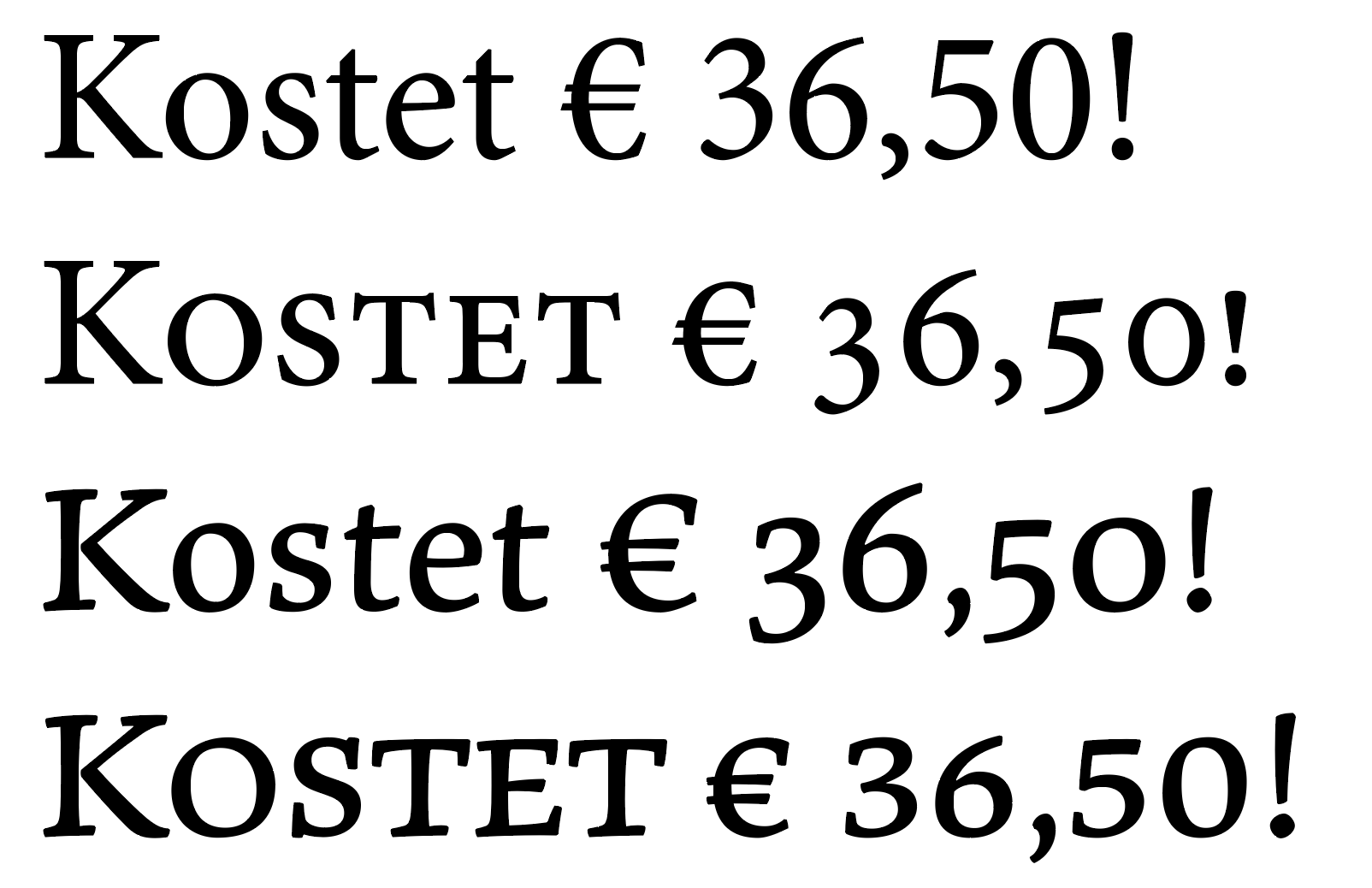
Erwartungen Kapitälchen-Belegung?
Mal ganz dumm gefragt: Was würdet ihr als Schriftanwender alles von einer Kapitälchenbelegung erwarten? Selbstredend sollte jeder Kleinbuchstabe ersetzt werden und der Wechsel auf passende Ziffern ist ebenfalls üblich. Aber danach wird es schnell schwammig. Was würdet ihr noch erwarten oder benötigen?
Eine ganze Menge weiterer Zeichen haben ja auch eher Versalhöhe: Währungszeichen, Satzzeichen, &, % etc. und spätestens bei »Alles in Kapitälchen« würden die dann unschön herausstechen und Kapitälchensatz gegebenenfalls unmöglich machen. Aber spielt das in euren Anwendungen überhaupt eine Rolle?
Ich verwende Kapitälchen eigentlich nur in Literaturverzeichnissen bzw. in Quellenangaben, daher reichen mir die alphanumerischen Glyphen, ggf. mit der üblichen Anpassung, früher ß zu Doppel-S und iota subscriptum zu adscriptum (ich sehe in neueren Schriften das adscriptum zugunsten des subscriptum schwinden, bin da jedoch epigraphisch geprägt).
Absolut. Ich freue mich immer sehr, wenn beim Umstellen auf OpenType → Kapitälchen vom Schriftgestalter (nicht nur die Versalhöhen-Zeichen wie
( ) / ? ! * % usw. mitgedacht wurde, sondern auch die Zeichen wie
+ - — # @ sowie An- und Abführungszeichen.
Versal-ß lasse ich mal wegen der besonderen Brisanz in diesem Forum unerwähnt ;-)
(Ein gutes Beispiel für nützliche diese »case sensive glyphs« ist die kürzlich erworbene Moniker.)
Zudem erwarte ich (ich weiß allerdings gar nicht, ob dass bei der OT-Umschaltung auf Kapitälchen nicht inzwischen ohnehin Standard ist), dass Groß und Kleinbuchstaben dann identische Höhen haben. Anders, als das früher bei vielen Caps-Schnitten (z.B. TheSans Caps) der Fall war.
Und da es selbst bei Foundries wie FontFont keine Selbstverständlichkeit zu sein scheint, bitte dann alles auch für die kursiven Schnitte – zum Beispiel für Markennamen, die in Versalien gesetzt sind, aber im Fließtext (so auch in kursiv gesetzten Zitaten) nicht so herausstechen sollen.
Mal abgesehen von dem "strg+a -> Alles in Kapitälchen"-Können, ist es überhaupt legitim, komplette Sätze in Kapitälchen zu setzen (mal von dieser angelsächsischen optischen Belästigung in EULA abgesehen)?
Ich habe die bisher als eine Art "Reserve-Auszeichung" verstanden, nicht als ein gewöhnliches Stilmittel, so dass auch nicht die komplette Bandbreite an Glyphen unterstützt werden müsste.
Ich erwarte, dass alle gebräuchlichen Anwendungen (die Ligatur & beispielsweise) umgesetzt sind.
Das Unterstützen von allem Möglichen verführt jedoch dazu, Kapitälchen auch unpassend einzusetzen bzw. die Wirkung durch die beliebige Anwendung aufzuweichen.
Für & gibt es vielfältige Anwendungen, aber für €? Oder gar %?
Ich verstehe Deinen Gedanken. Aber dieser Argumentation folgend, dürfte ja dann auch für den echten Versalsatz nicht alles passend vorhanden sein, oder? Man händigt den Leuten ja auch nicht nur Minimalrationen Salz aus damit sie ihre Suppe ja nicht versalzen bzw. nur die echten Köche verstehen richtig damit umzugehen. 😬
Kommt natürlich auch immer darauf an, was man erreichen möchte: Wenn eine Satzschrift auf den Markt gebracht werden soll, die möglichst erfolgreich werden und umfangreichsten Ansprüchen standhalten soll, würde ich wohl nach dem Motto vorgehen: Besser man hat, als man hätte. 🤷🏼‍♂️
Besser man hat, als man hätte.
Hehe, ja, das ist auch immer mein Gedanke, wenn ich sehe, dass eine Schrift griechisch kann, dann aber sehe, dass nur monotonisches Griechisch unterstützt wird.
vor 58 Minuten schrieb Martin Schulz:
dass Groß und Kleinbuchstaben dann identische Höhen haben
Meinst Du damit nicht Versalsatz? Der Sinn von Kapitälchen ist doch, dass die Gemischschreibung erhalten bleibt, obwohl nur formale Versalien genutzt werden. Oder bringe ich da was durcheinander?
vor 19 Minuten schrieb R::bert:
dürfte ja dann auch für den echten Versalsatz nicht alles passend vorhanden sein, oder?
Ich stehe da vielleicht echt auf dem Schlauch, aber für den Versalsatz ist doch auch vieles nicht vorhanden, ich kann mich beispielsweise nicht an ein versales & erinnern.
vor 1 Stunde schrieb Martin Schulz:
Versal-ß lasse ich mal wegen der besonderen Brisanz in diesem Forum unerwähnt
Ehrlich gesagt, würde ich hier mir stets die Wahl zwischen SS und ẞ wünschen, damit ich die Möglichkeit hätte, den historischen Gebrauch abzubilden wie beispielsweise beim Teehaus Maass (hieß der Mensch tatsächlich Maass (ich kenne das von Menschen, die nach irgendeinem alten Standard gelernt haben, bei Schreibmaschinen ohne ß dieses so ersetzten) oder vielleicht eher Maß?).tee-maass.png.d7e9b82ed265f7a53802087d24ce251c.png
Am 12.2.2023 um 15:25 schrieb Phoibos:
Der Sinn von Kapitälchen ist doch, dass die Gemischschreibung erhalten bleibt, obwohl nur formale Versalien genutzt werden. Oder bringe ich da was durcheinander?
Am 12.2.2023 um 16:12 schrieb Ralf Herrmann:
Die Minion hat ein verkleinertes €, das aber immer noch größer ist als die Kapitälchen und ein kleines Ausrufezeichen.
Cool, das ist mir noch nicht aufgefallen. Vielen Dank für den Hinweis.